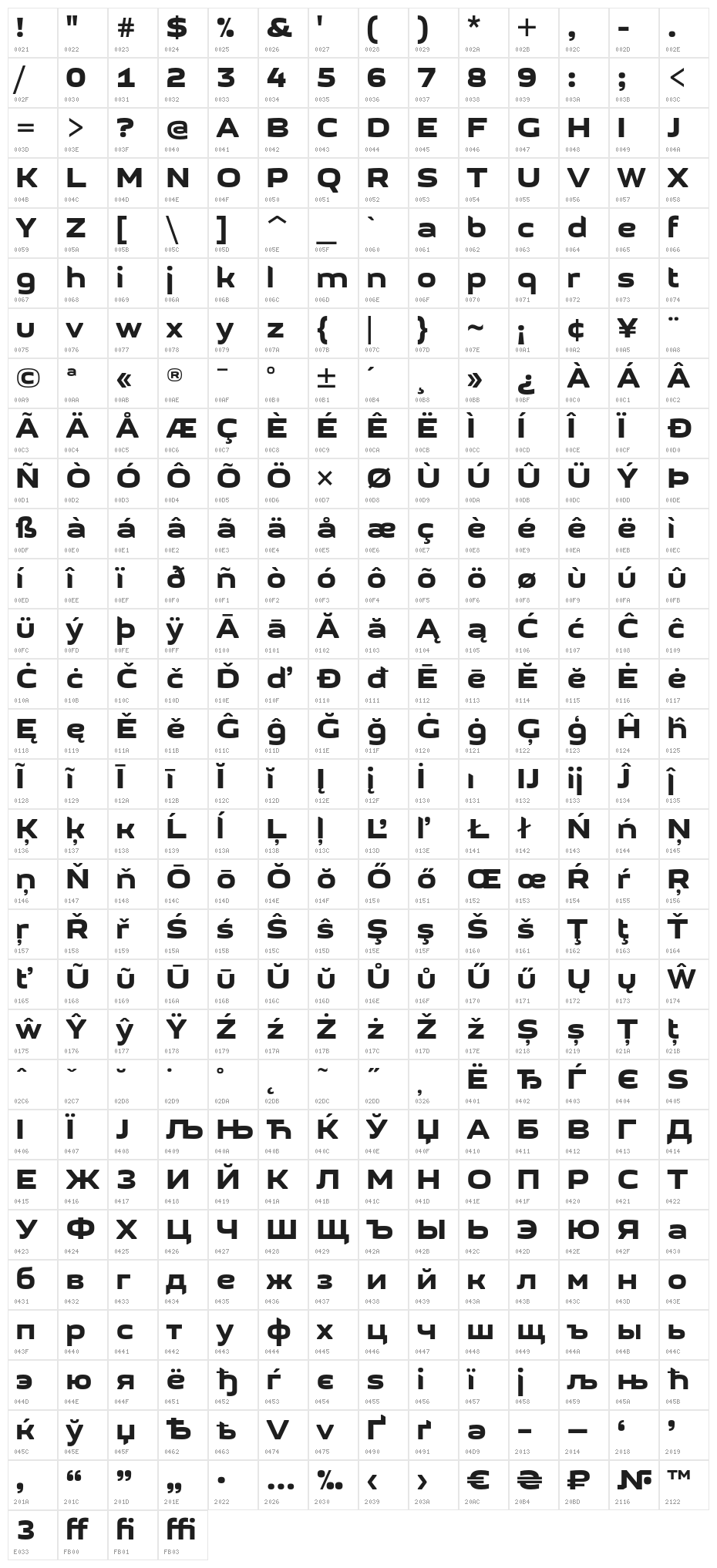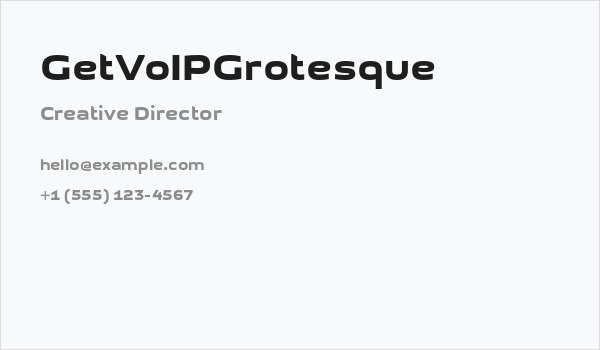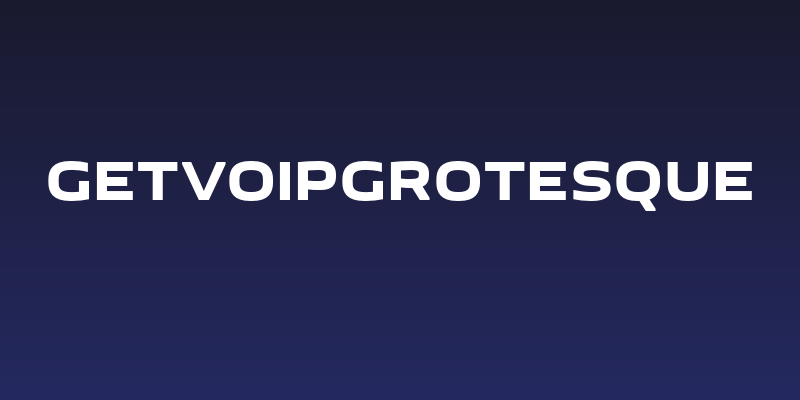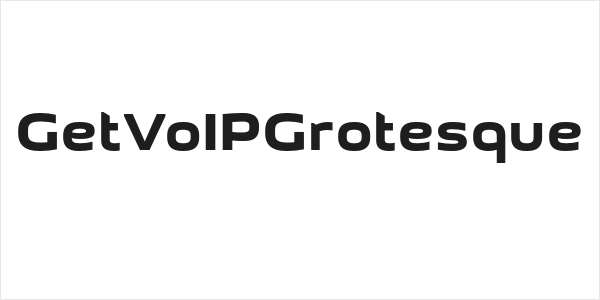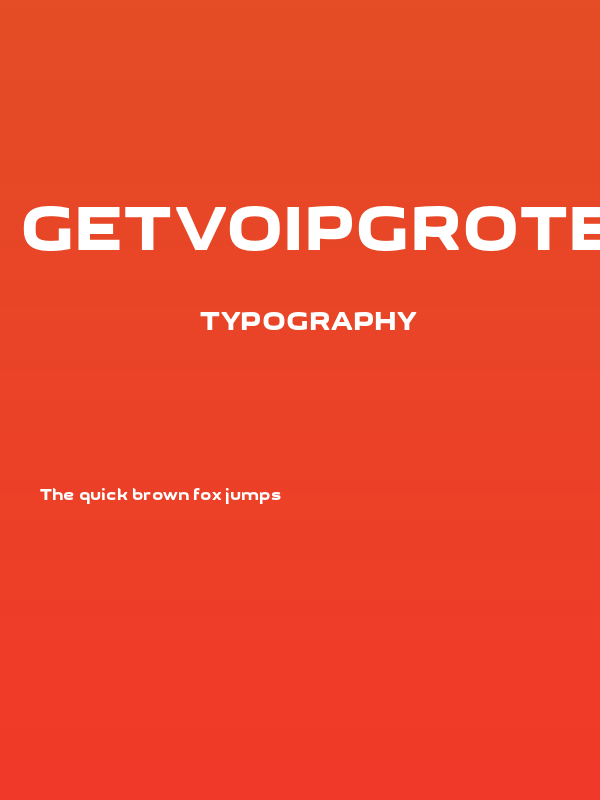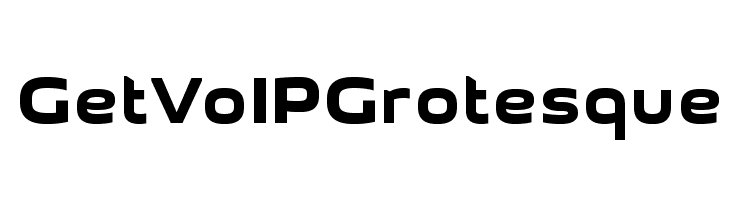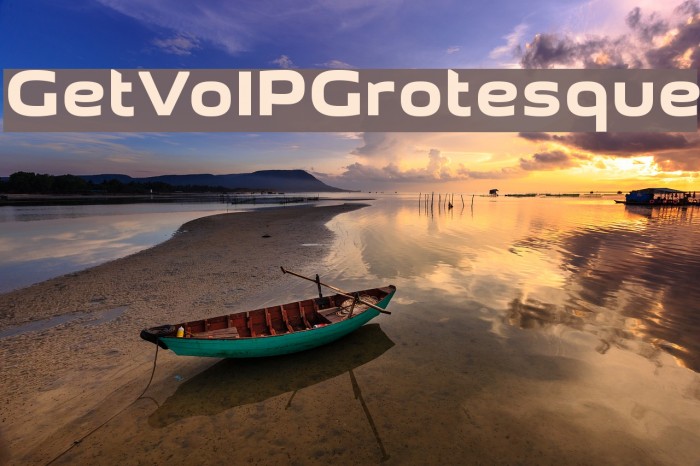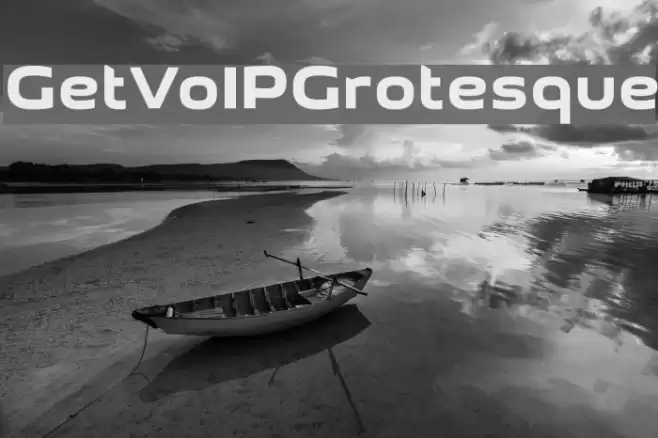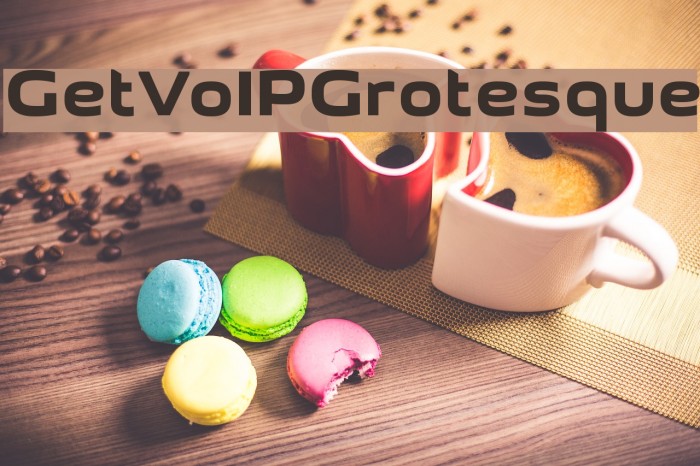
GetVoIPGrotesque Font
| Cas d'utilisation | Headlines, Logos, Digital media |
| Projets proposés | Ideal for branding, advertising, web design, and editorial projects where a modern and bold typeface is required. |
| Auteur | Fonts by Måns Grebäck |